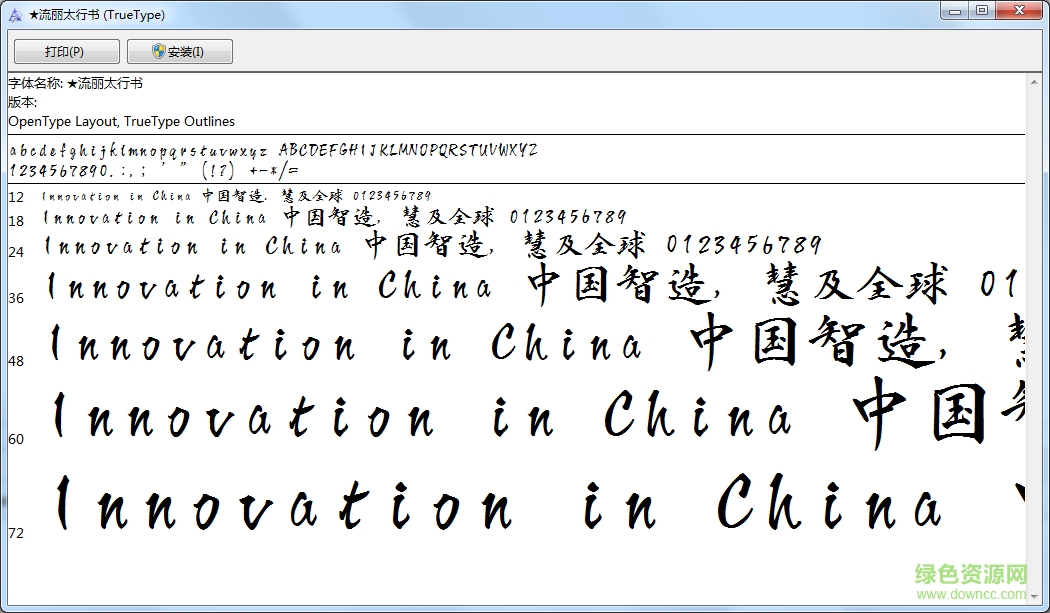
流麗太行書字體
流麗太行書體是一款非常實(shí)用的字體,字體整體清新自然,字體間距較大,看著非常的輕松,筆畫纖細(xì)優(yōu)雅,非常的實(shí)用,歡迎有需要的朋友到綠色資源網(wǎng)下載使用吧!
字體威武有形,力道十足,可應(yīng)用于繪畫設(shè)計(jì)、藝術(shù)創(chuàng)作、平面廣告、印刷包裝等領(lǐng)域